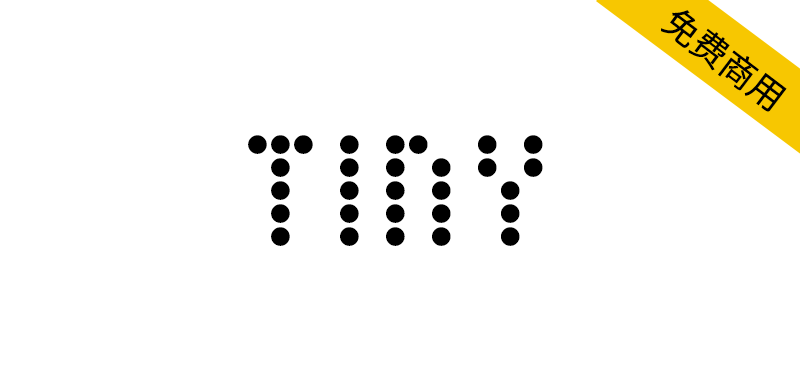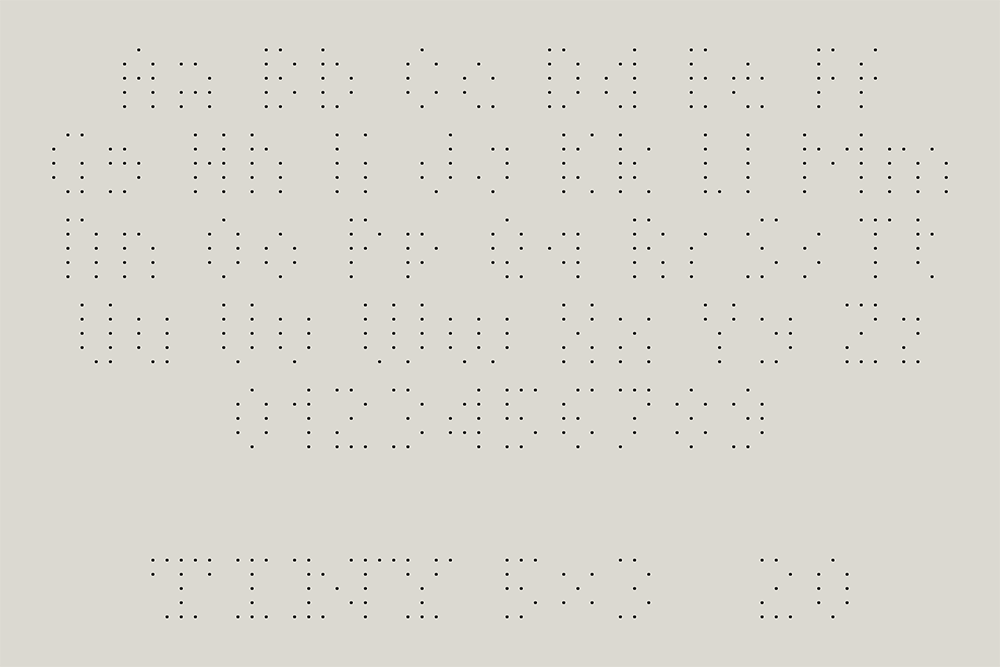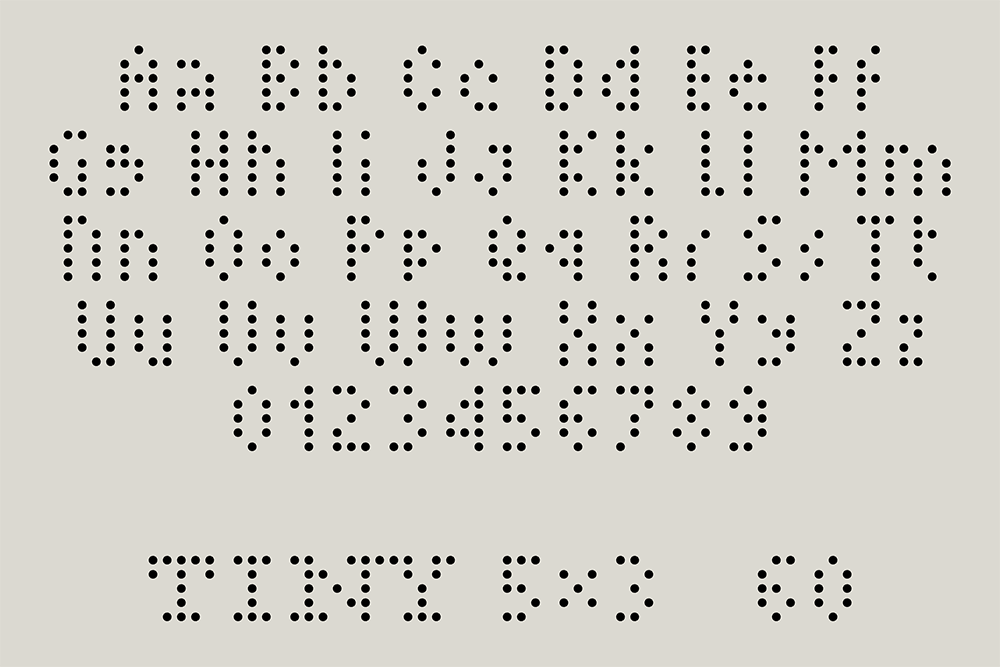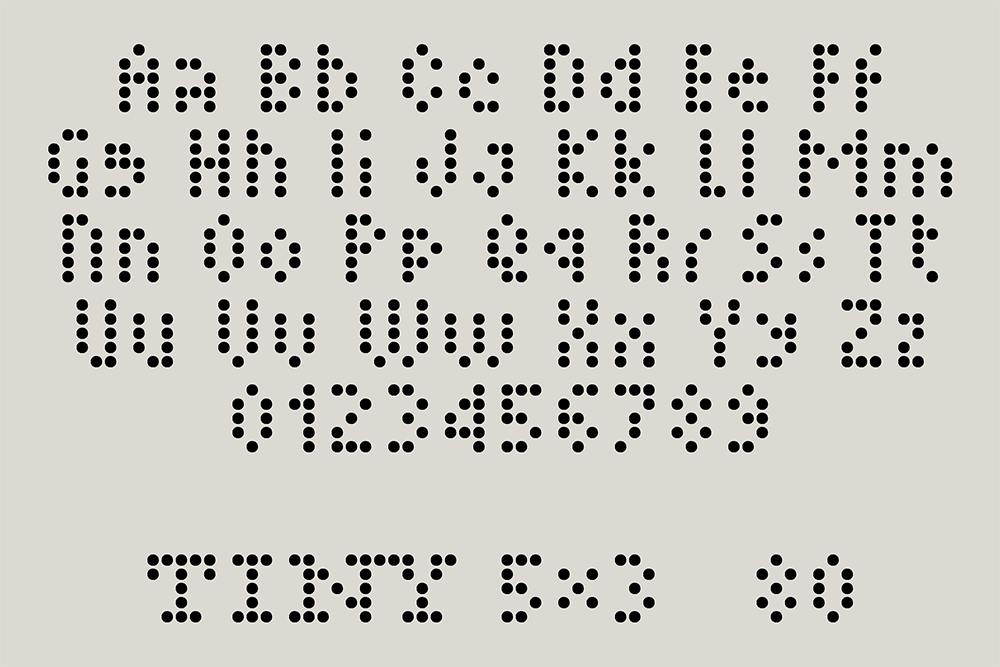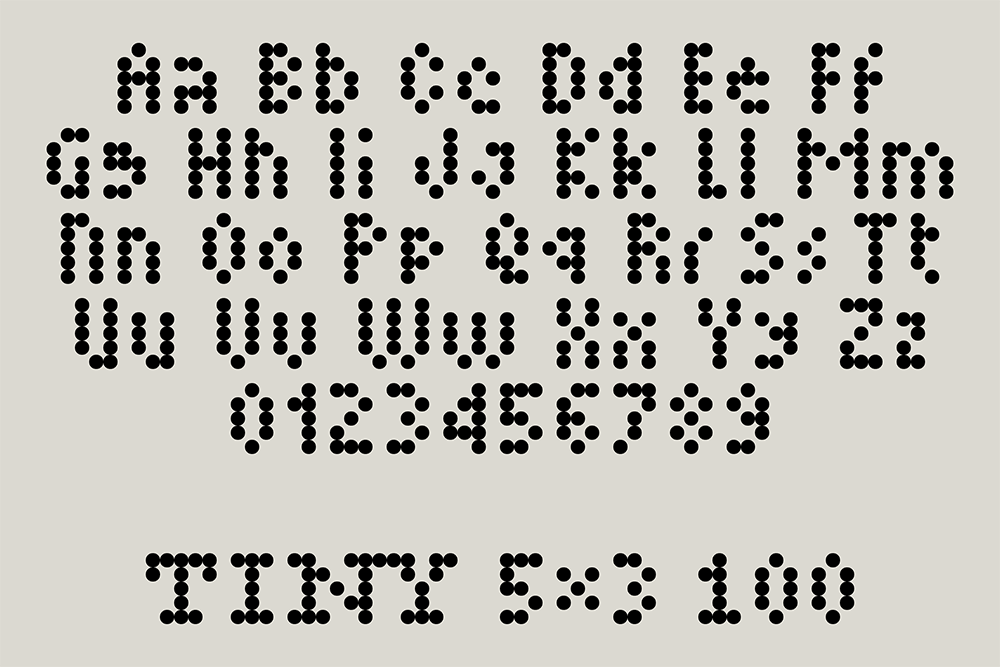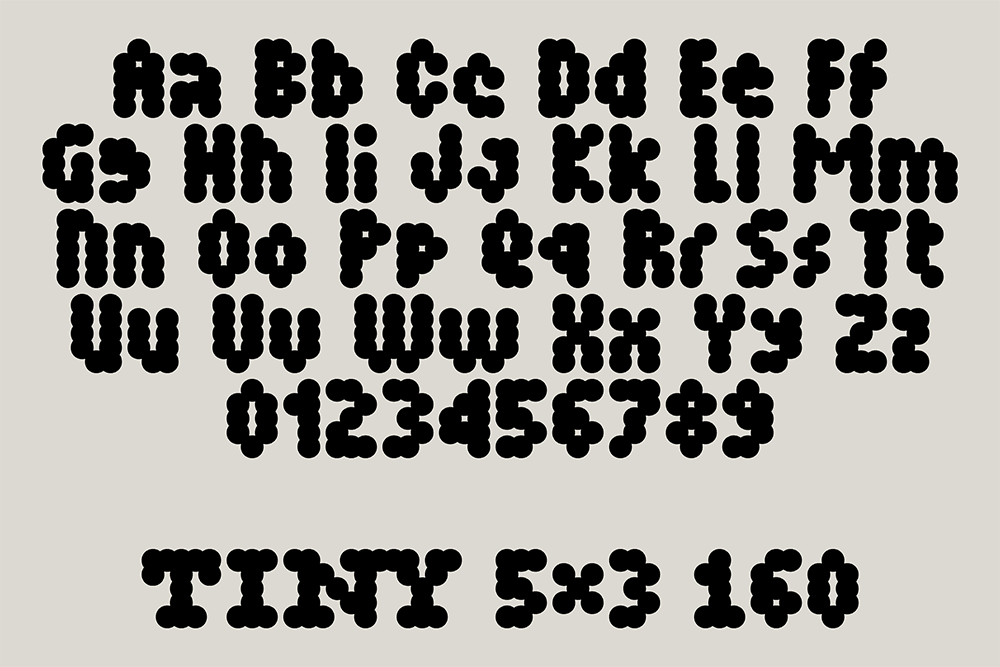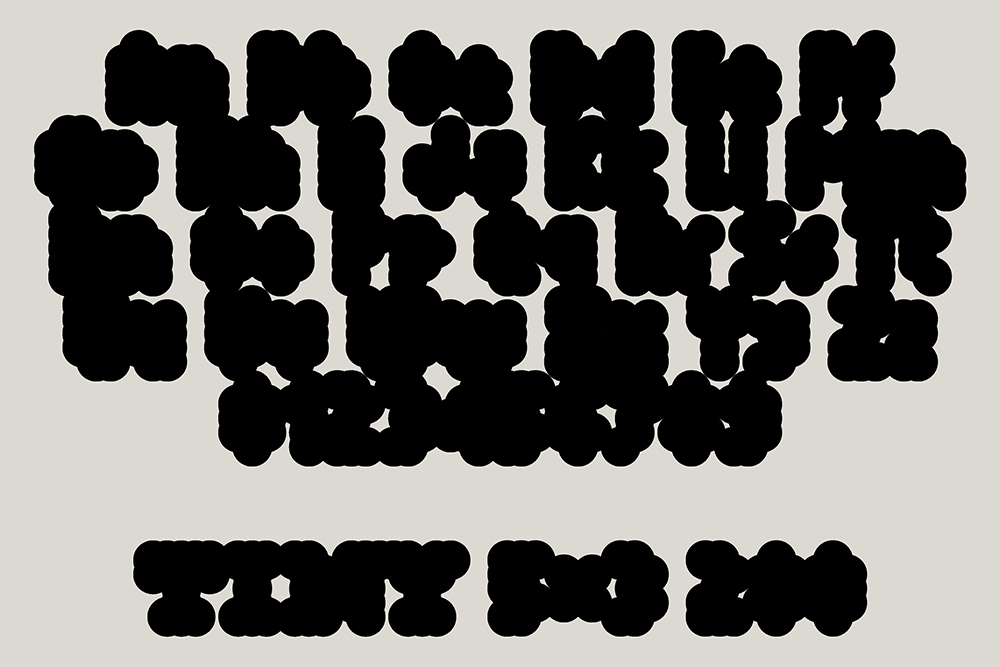
TINY字体家族最初是在2018年夏天创建的,作为纽约市唐人街一家名为“Today in New York”(简称TINY)的实验性零售快闪店的视觉标识。这家商店是创意机构Verdes的一个实习项目的结果,Jack Halten Fahnestock和Théia Flynn在那里出售现场定制的T恤和手提包。TINY基于HandJet EBS-250的最小字体尺寸(仅使用16个可用打印头中的5个),HandJet EBS-150是商店中用于在纺织品上立即打印的工具。其可变墨点大小来自HandJet的可调墨水输出。
TINY 5x3是一种可变字体,具有一个大小轴,可以从0-300修改点大小,以及15个单独的实例(每个实例将点大小增加20个单位)。
字符集1300 +符号:虽然目前只有拉丁语,但字符有很多;各种风格;广泛的标点符号,包括区分大小写的形式;上标数字、(unicase)字母和一些标点符号;小写大写(unicase);包括分数在内的数学字符;比例图、旧式图和表格图;罗马数字;箭头数天;各种各样的符号。
The TINY font family was originally created over the summer of 2018 as the visual identity for an experimental retail pop-up shop in Chinatown, New York City called “Today in New York”, or TINY for short. The shop was the result of an intern project at Verdes, a creative agency, between Jack Halten Fahnestock and Théïa Flynn, where they sold T-shirts and tote bags customized on the spot. TINY is based on the smallest type size (using only 5 of the 16 available print heads) of the HandJet EBS-250, the tool used in the shop for immediate printing on textiles. Its variable dot size comes from the HandJet’s adjustable ink output.
TINY 5x3 comes as a variable font with a size axis to modify dot size from 0—300, as well as 15 separate instances (each increasing the dot size by 20 units).
Character Set 1300+ glyphs,Included: only Latin-based languages for now but a lot of ’em; various styles (see section below); extensive punctuation including case-sensitive forms; superscript numbers, (unicase) letters, and some punctuation; small caps (unicase); math characters including fractions; proportional, oldstyle, and tabular figures; roman numerals; arrows for days; miscellaneous symbols